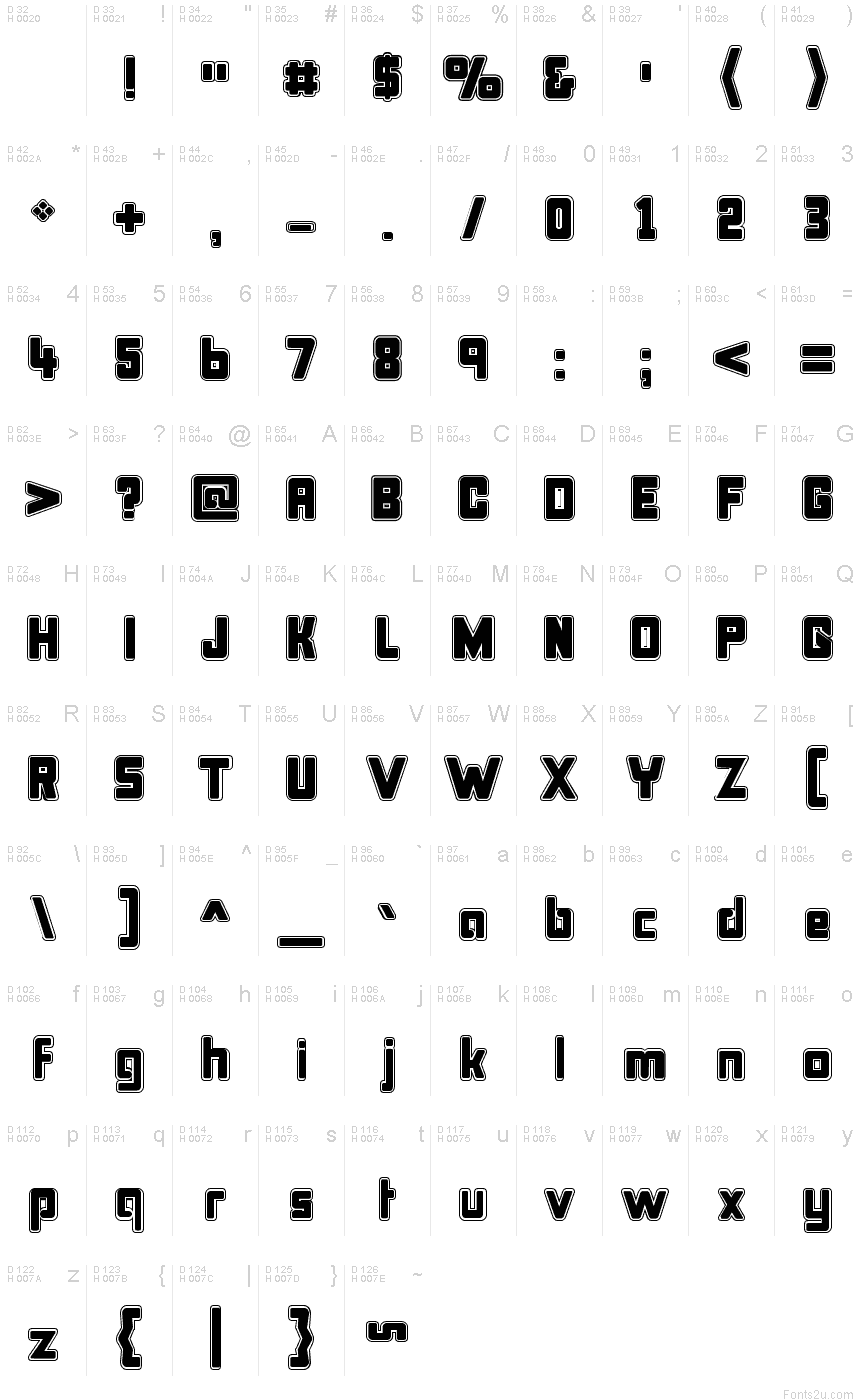
Bonk College autorstwa Rolfa Schoebera z GemFonts to darmowy, dekoracyjny krój pisma o śmiałej, kreskówkowej energii. Jego grube, zaokrąglone kształty przypominają wypukłe litery w stylu uniwersyteckim połączone z graffiti typu bubble, a wszystko to w czystym obrysie, dzięki któremu każde słowo dosłownie wyskakuje z kartki. Masywny rytm i duże światła wewnątrz liter sprawiają, że pismo jest wyraziste, a jednocześnie łatwe w odbiorze nawet przy szybkim spojrzeniu.
Używając Bonk College, zmienisz nagłówki w zabawne hasła w tytułach gier, plakatach w stylu college'owym, brandingu imprez dla dzieci, zaproszeniach, miniaturach na YouTube czy opakowaniach przekąsek i zabawek. Ten darmowy font najlepiej sprawdza się w dużych i grubych rozmiarach; w mniejszych tekstach zestaw go z prostym, geometrycznym bezszeryfowym krojem, aby zachować równowagę i czytelność projektów.
Bonk College